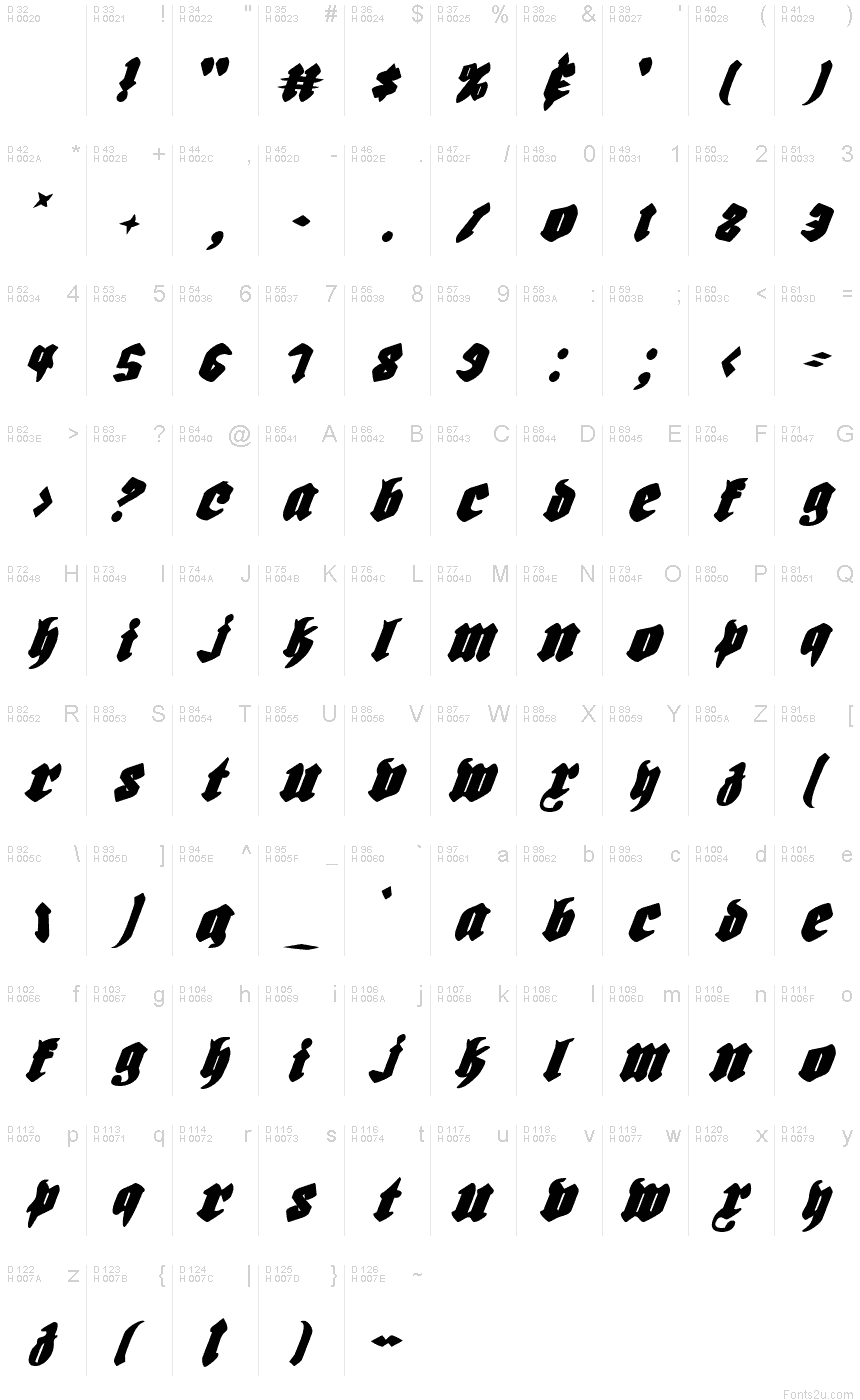
Biergarten Italic od Iconian Fonts to darmowy, średniowieczny krój gotycki, który oddaje charakter dawnych szyldów piwiarnianych. Litery pochylają się do przodu w ciężkich formach blackletter, łącząc ostre, rzeźbione krawędzie z zaokrąglonymi, pełnymi kształtami, co nadaje teksturze gęsty i żywy charakter.
Doskonale pasuje do identyfikacji wizualnej pubów, plakatów na Oktoberfest, okładek płyt, nagłówków menu czy ulotek imprezowych, gdzie potrzebny jest darmowy font z historycznym klimatem. Wykorzystaj go w krótkich nagłówkach, nazwach na etykietach czy tytułach; ten pochylony, zwarty rytm sprawia, że nawet kilka słów nabiera wyglądu szyldu namalowanego dla starej tawerny.
Biergärten Italic